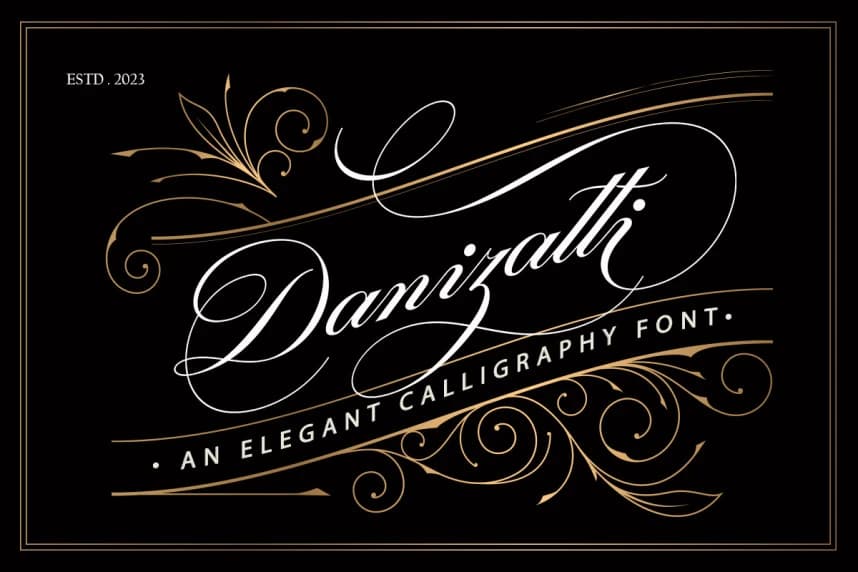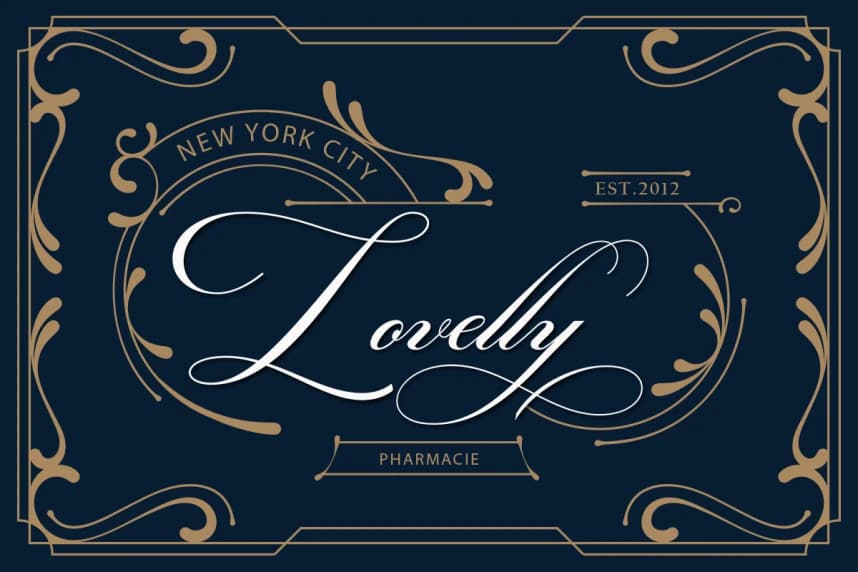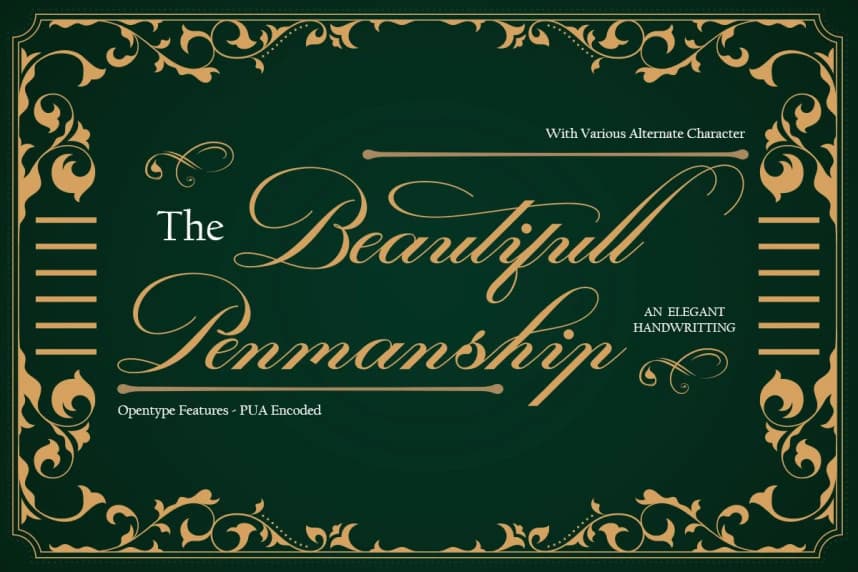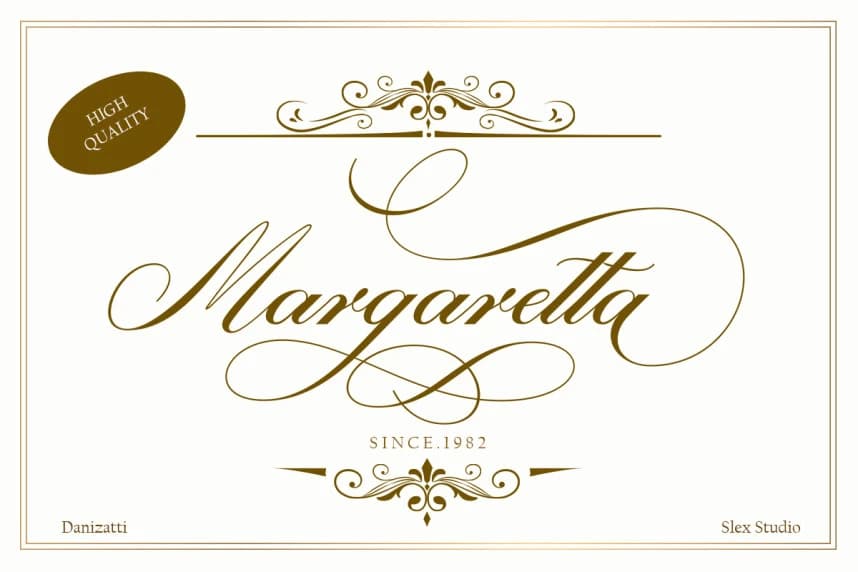
Dannizatti Script Font
Dannizatti Script Font. Çok zarif bir yazı tipi yaratmak istiyorum. Bu yüzden Danizatti Script'i yarattım; modern bir dokunuşla klasik dekoratif bir yazı tipidir. Bu, vintage logolar, moda etiketleri, özel kart başlıkları, rozetler, gıda ambalajı tasarımları ve özellikle şarap etiketleri için tasarl
Dannizatti Script Font. Bir yazı tipi yaratmak istiyorum; bu çok zarif. Bu yüzden Danizatti Script, modern bir dokunuşa sahip klasik dekoratif bir yazı tipinin bir türü. Bu, vintage logolar, moda etiketleri, özel kart başlıkları, rozetler, gıda ambalaj tasarımları için tasarlanmış bir gösterim yazı tipidir; özellikle şarap etiketleri için.
Dannizatti Script